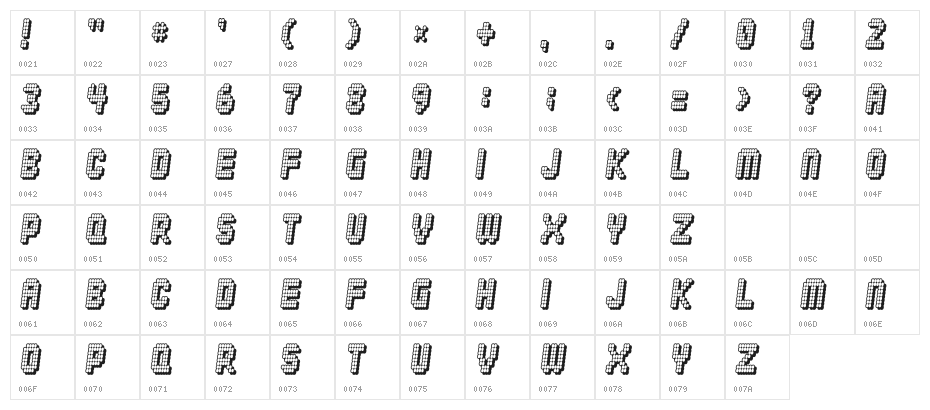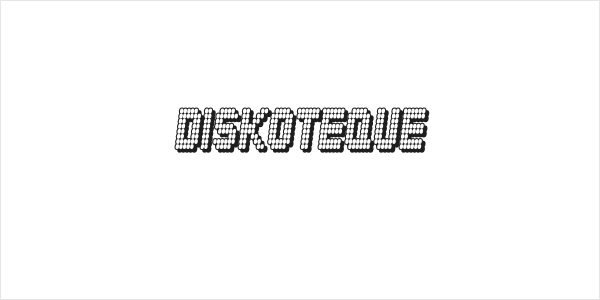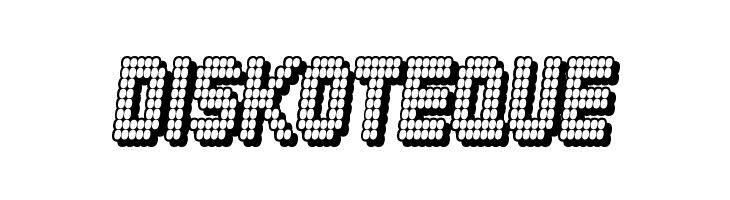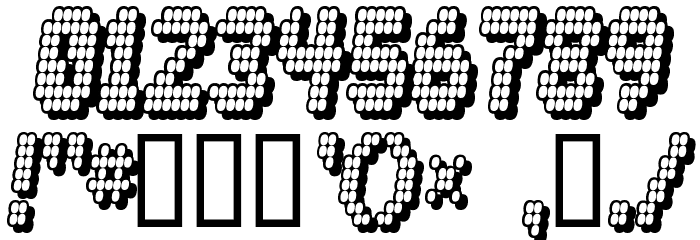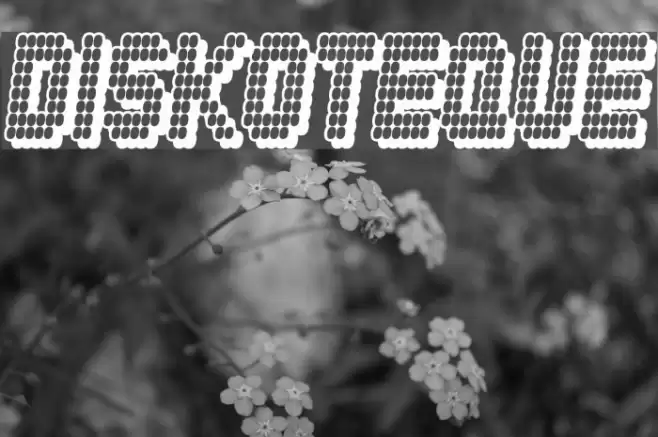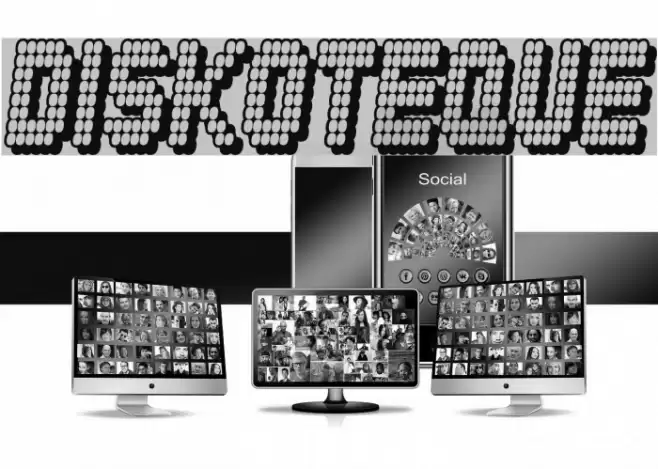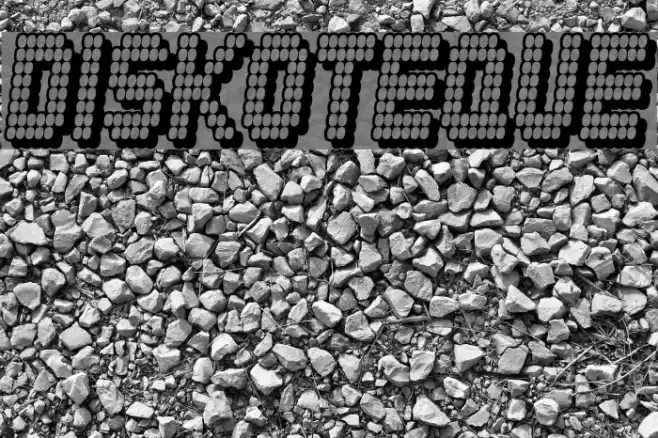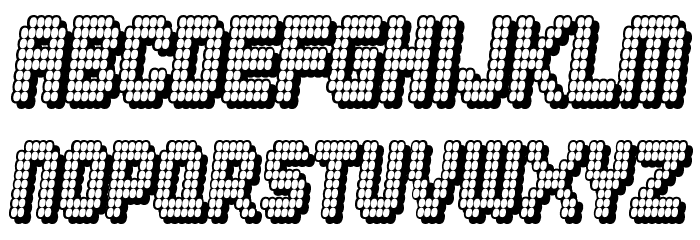
Diskoteque Font
✎ Dotted
| Estilo general | Retro, Modern |
| Proyectos propuestos | Ideal for event posters, party invitations, digital displays, retro-themed designs, and branding projects that require a fun and engaging aesthetic. |